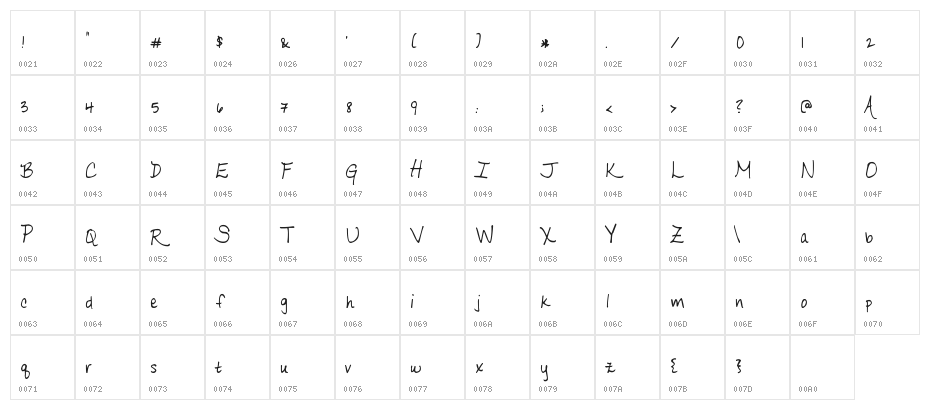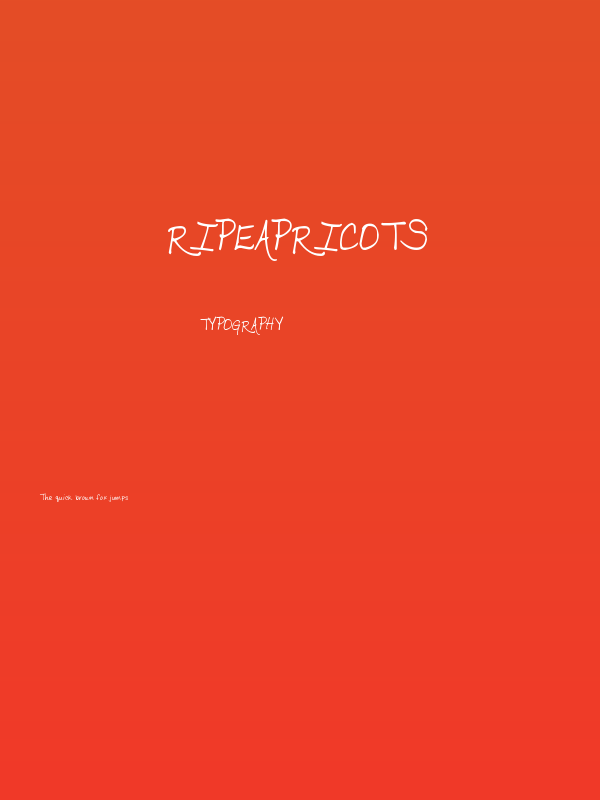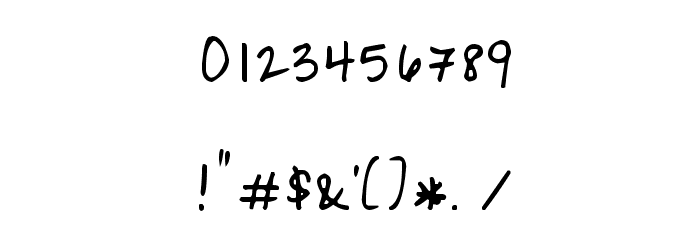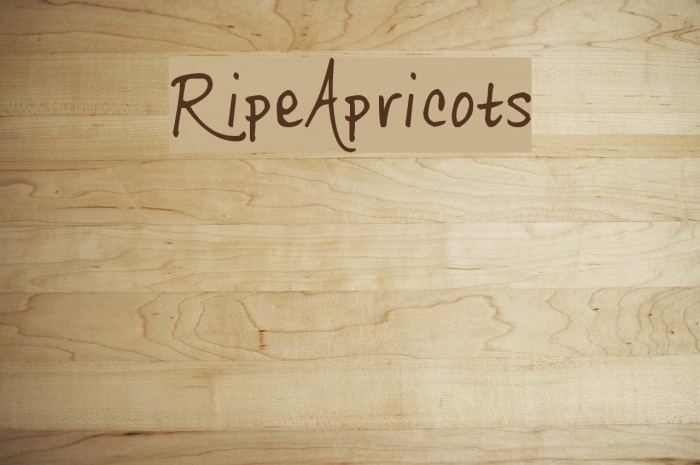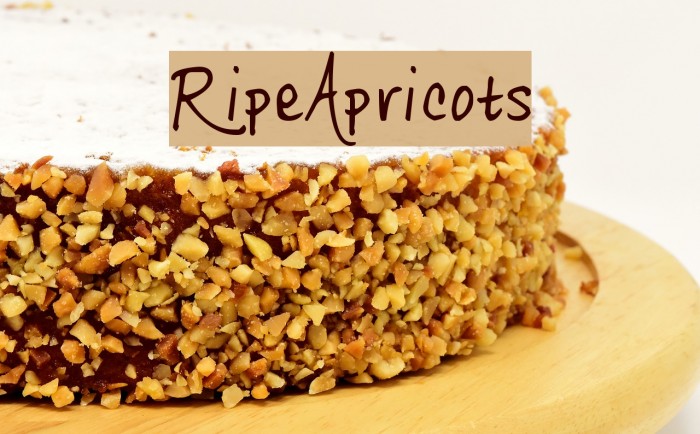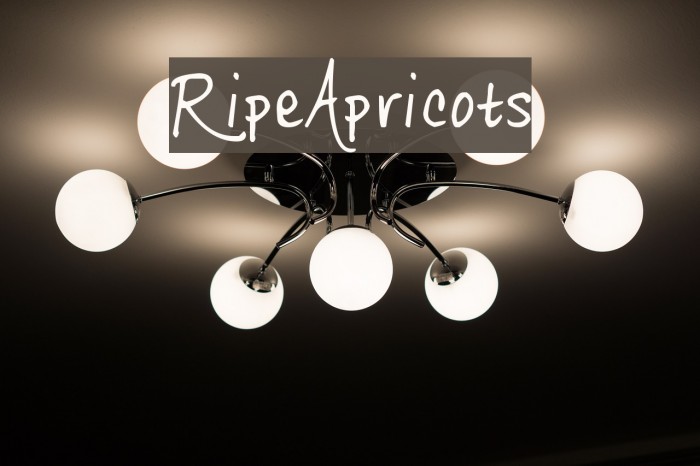
RipeApricots Font
Fonts by Xerographer Fonts
このフォントには 92 文字が含まれています。文字をクリックして詳細を表示。
| 全体的なスタイル | Casual, Playful |
| 用途 | Headlines, Logos, Invitations |
| おすすめプロジェクト | Great for greeting cards, personal branding, children's books, and casual invitations. |